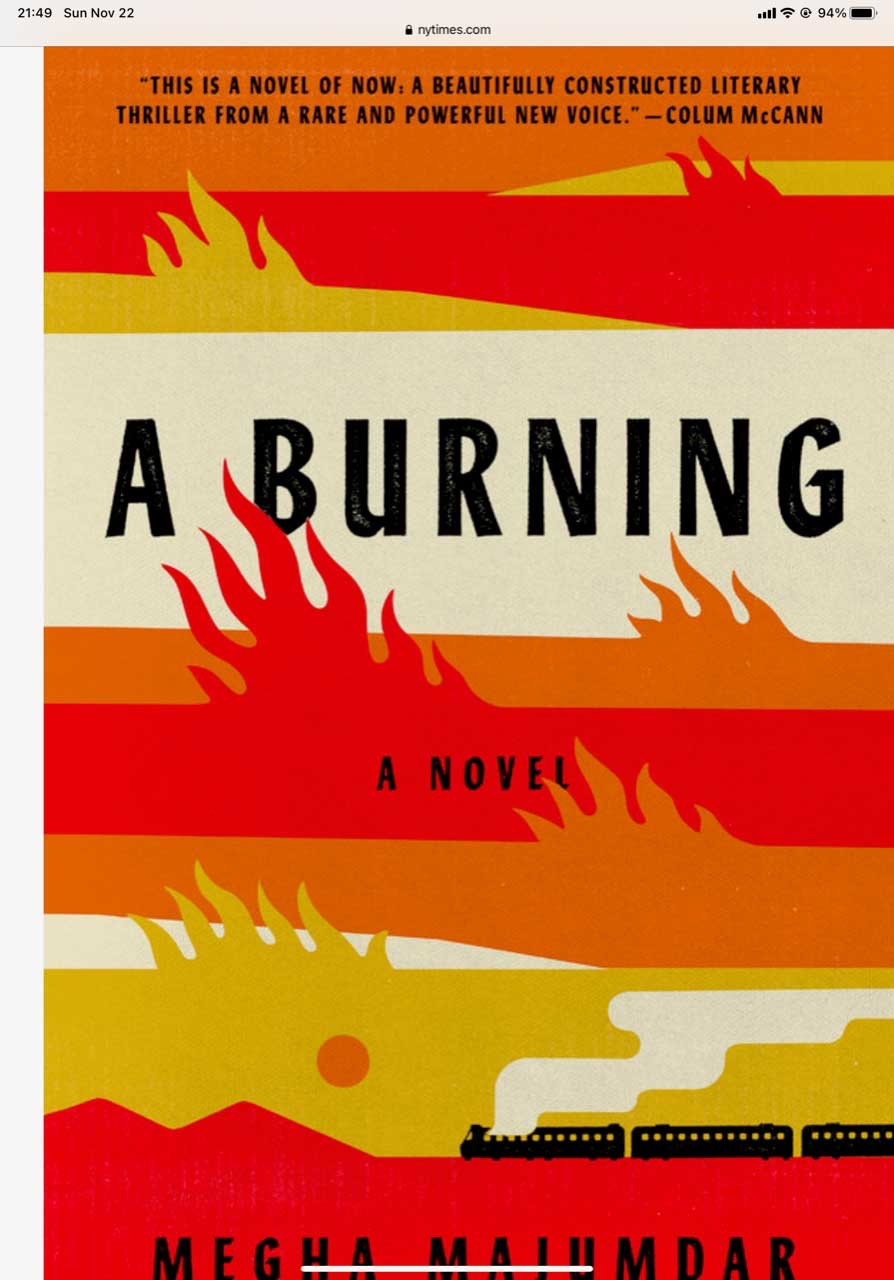
Coverschrift von "A Burning"
kennt jemand ad hoc die Schrift auf dem Cover? Könnte natürlich handgemalt sein. WhatTheFont hat nichts passendes geliefert.
Super, der "Alterungseffekt" ist dann vermutlich via Photoshop dazugemacht worden.